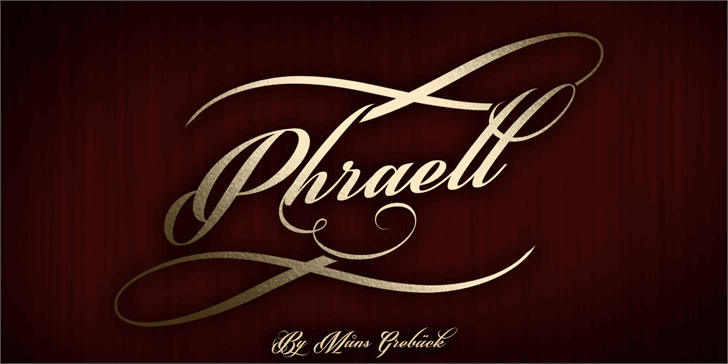
Descubra a elegância e a versatilidade do Phraell Font na sua próxima projeto de design. Especialmente projetado para designers que valorizam uma tipografia fluida, este script font é perfeito para criar um estilo moderno e sofisticado em seus trabalhos. Ideal tanto para textos como para logotipos, o Phraell oferece uma combinação única de linhas delicadas e formas arredondadas que fazem dele um favorito entre os criativos. Fornecido por Hamilton, este font é a escolha perfeita para qualquer designer que busca qualidade em cada caractere. Para adquirir sua licença comercial, visite o site oficial: www.mansgreback.com/phraell. Descubra hoje mesmo como transformar seu design em algo excepcional com Phraell Font.